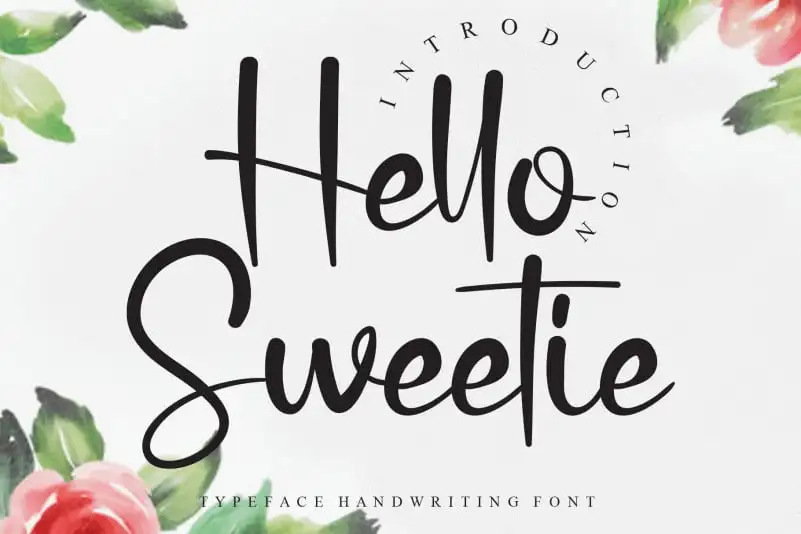
Hello Sweetie Script Font – Download Grátis
A fonte ‘Hello Sweetie Script Font’ é uma escolha perfeita para aqueles que buscam adicionar um toque suave e delicado a suas criações digitais. Desenvolvida pelo designer creativeletter, esta linha elegante e curvilínea oferece um design handwritten único, ideal para criar mensagens pessoais ou frases românticas. Composta por linhas leves que se fundem em uma harmoniosa textura, a ‘Hello Sweetie Script Font’ permite aos designers explorar uma linguagem de escrita única e autêntica. Seja você criando cartões de aniversário personalizados ou qualquer tipo de documento onde um estilo handwritten romântico seja desejado, esta fonte será uma escolha brilhante. Especializada em dar uma experiência excepcional a seus usuários finais, ela é perfeita para aqueles que buscam adicionar um toque único e emocionante a seus projetos digitais. Seja você criando cartões de aniversário com detalhes encantadores ou escrevendo mensagens íntimas em uma página do seu diário pessoal, a ‘Hello Sweetie Script Font’ oferecerá um design handwritten autêntico que deixará sua marca.